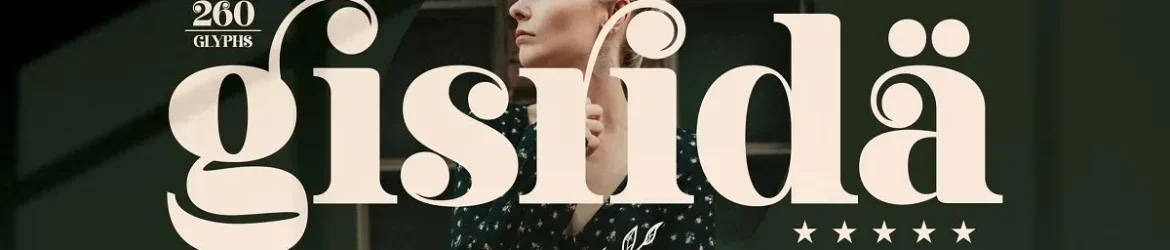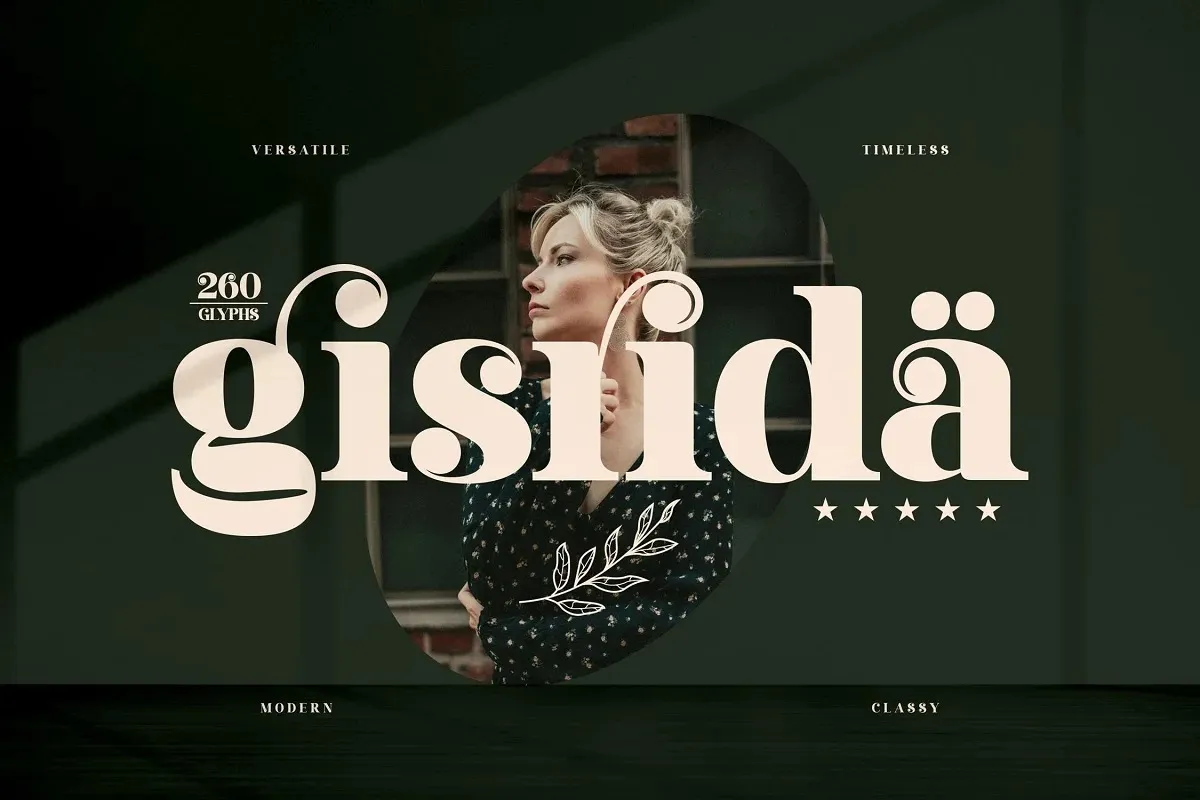
Gisrida Font – Fonte Grátis
Gisrida Font
A Gisrida Font é uma elegante tipografia serifada, com linhas afiadas que contêm curvas naturalmente belas. Perfeita para logotipos luxuosos e sofisticados, títulos de livros ou filmes, marcas de moda, revistas, selos de roupas, cartazes, citações e muito mais. Cada glyph da Westiva foi projetado com esses encantadores contornos naturais que proporcionam uma aparência ainda mais refinada. Ideal para quem procura uma fonte que não apenas destacará sua marca, mas também a realça em um nível ímpar de elegância e luxo.